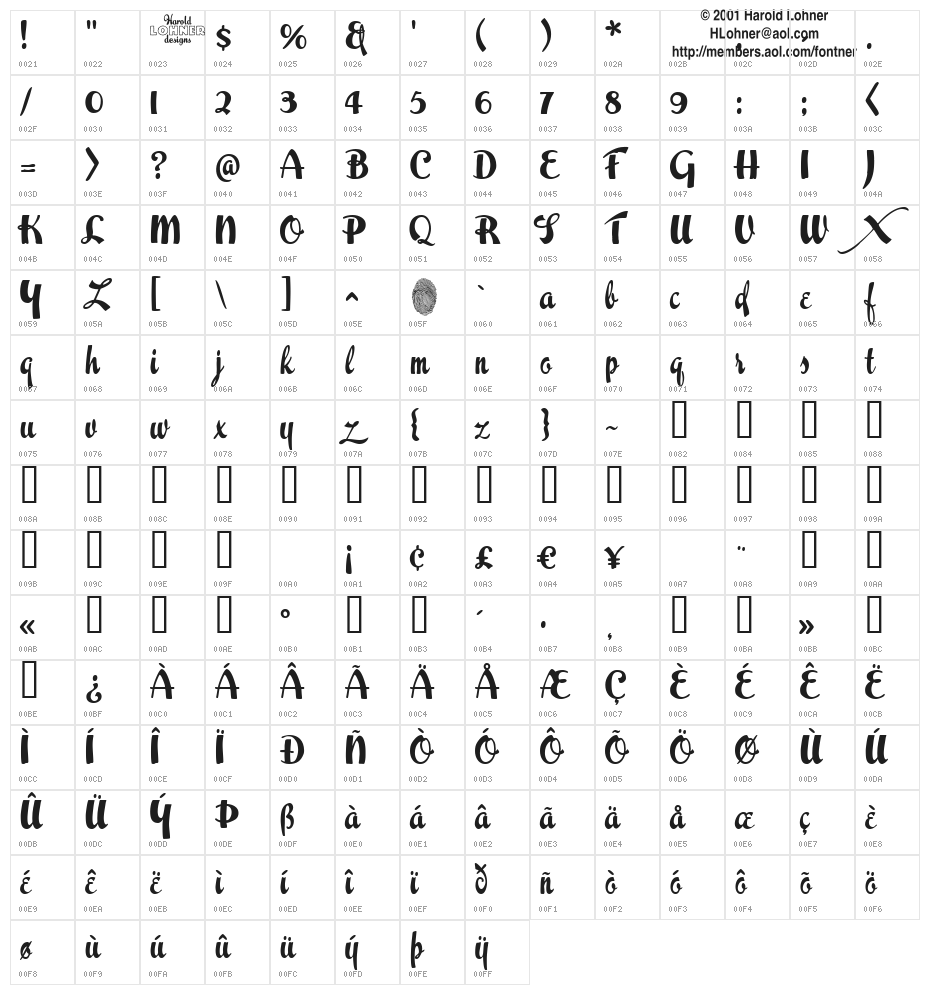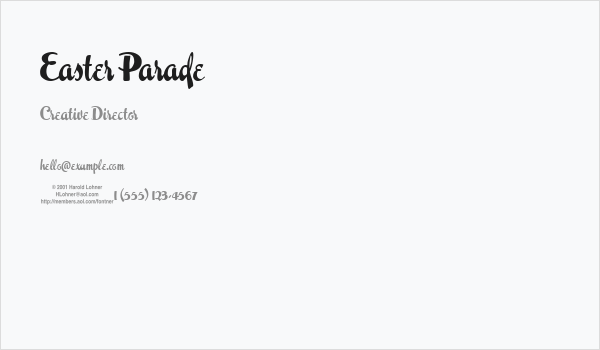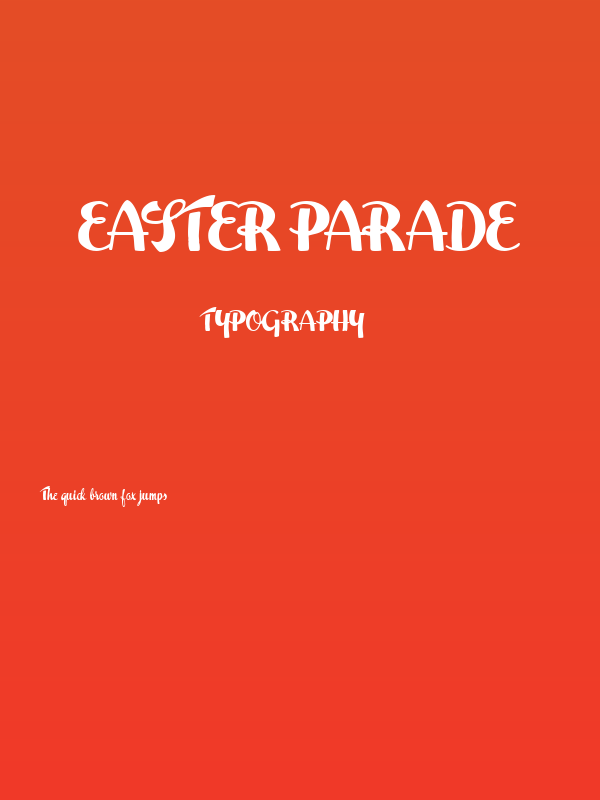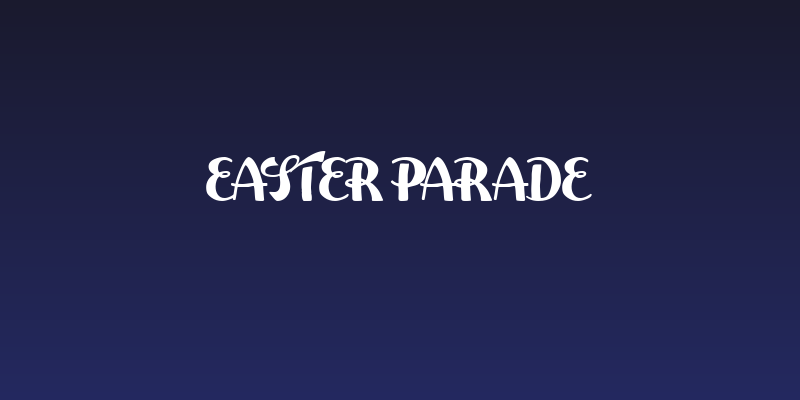
Easter Parade Font
| 用途 | Headlines, Logos, Invitations |
| おすすめプロジェクト | Ideal for greeting cards, invitations, posters, and branding projects that require a touch of whimsy and creativity. |